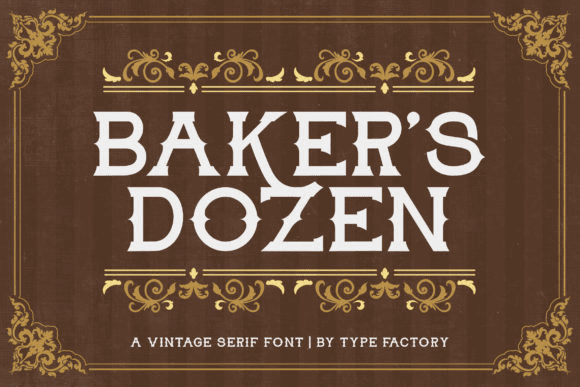
[Creativefabrica] Baker’s Dozen Font (2021)
Baker's Dozen - красивый шрифт с засечками. Он сочетает в себе чувство классики, миловидности, элегантности и винтажности, что делает его достаточно выразительным, чтобы придать любому проекту жизнь и энергию, в которых он нуждается. Если вы ищете винтажный и уникальный шрифт, который привнесет в ваш проект много радости, то Baker's Dozen - идеальный шрифт для вас!